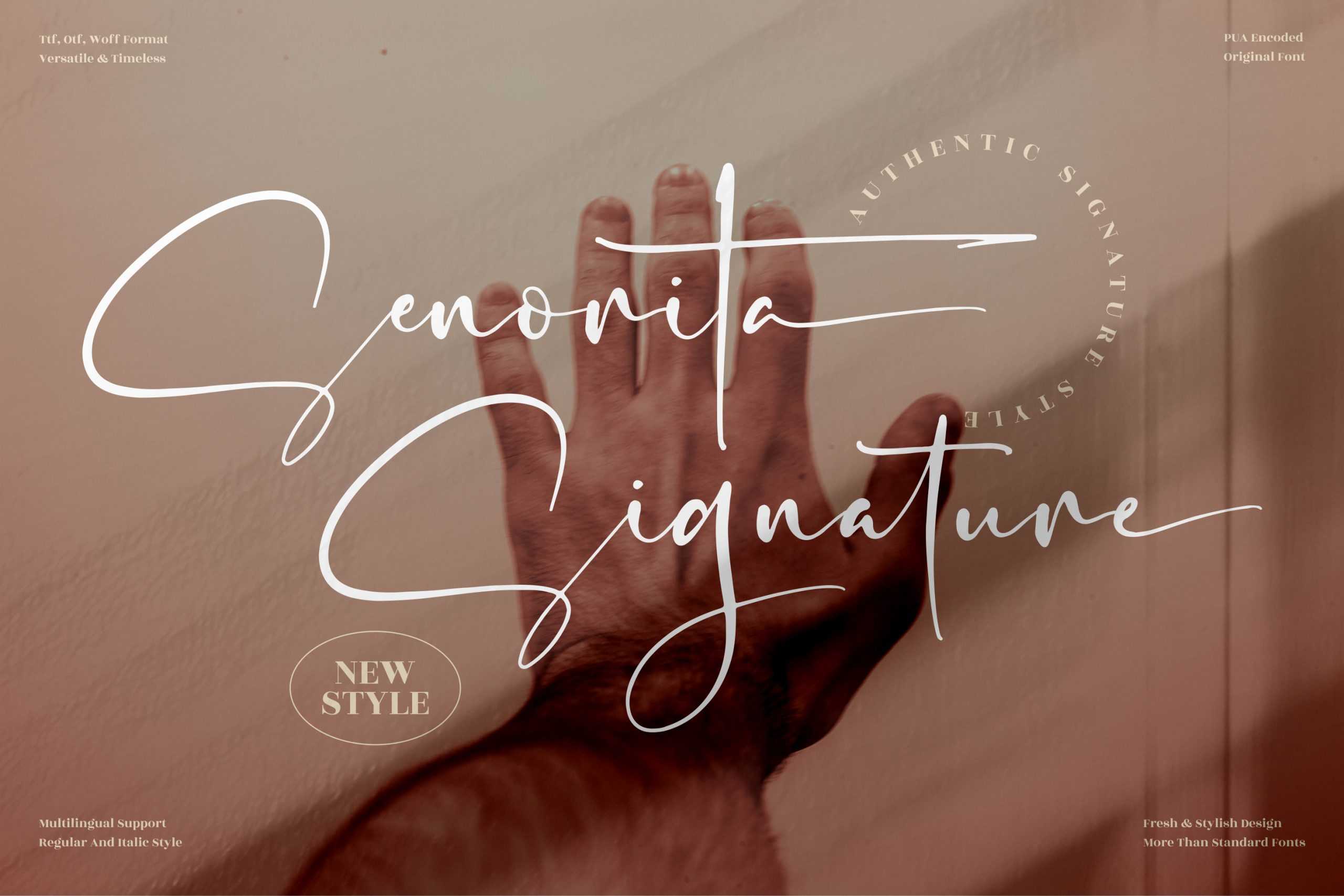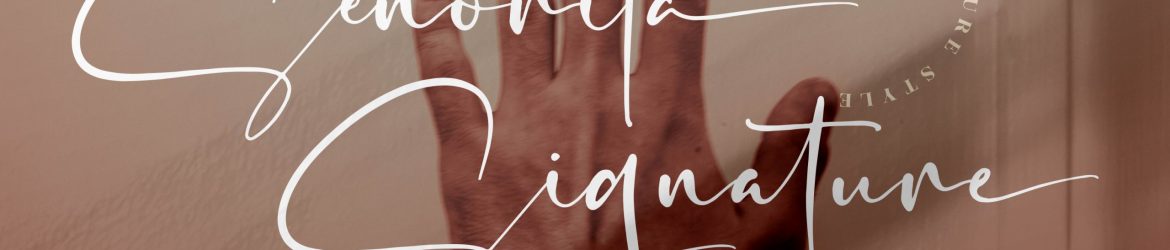
A Senorita Signature Font é uma opção excepcional para projetos criativos que buscam um toque sofisticado e elegante. Feita por designers experientes, essa fonte de escrevermanha perfeita para personalizar qualquer tipo de projeto. Ideal para criações visuais como logos, rótulos, embalagens, cartões de nome, cartas de convite e muito mais. Seja você um designer gráfico ou alguém que busca uma maneira única de dar vida a suas obras de arte em têxtil ou impressão digital, essa fonte irá oferecer-lhe um toque único e luxuoso. Ela é perfeita para o design de móveis de quarto, embalagens personalizadas e outros produtos que precisam de uma identidade única. Com a Senorita Signature Font, você pode conferir os limites da criatividade e trazer um toque sofisticado à sua arte. E se você está procurando por uma fonte que dê valor à sua marca ou produto, essa é definitivamente a escolha certa. Ela permite que você personalize seus projetos de maneira única, tornando-a perfeita para qualquer tipo de projeto que esteja buscando um acabamento premium e sofisticado.